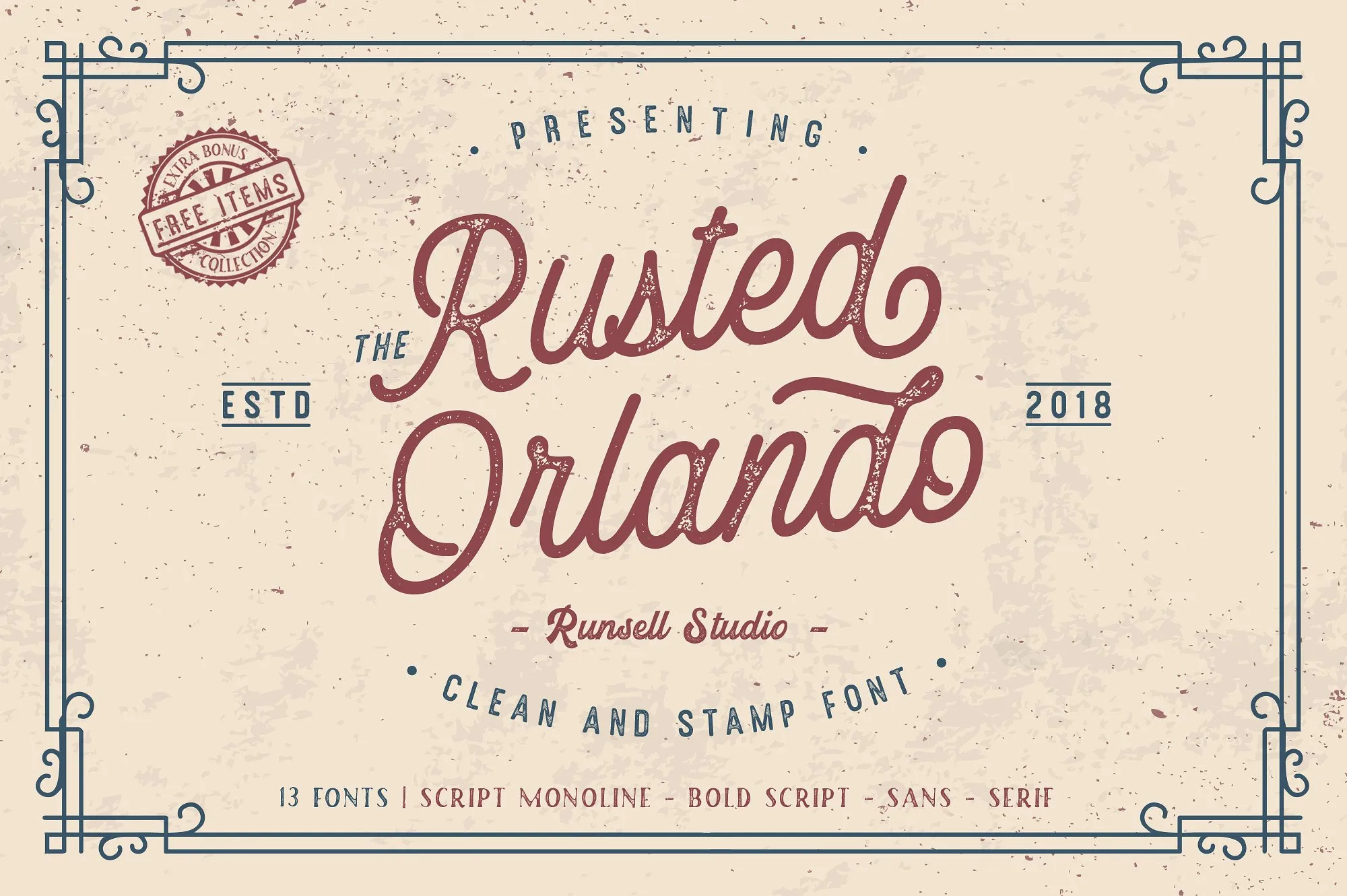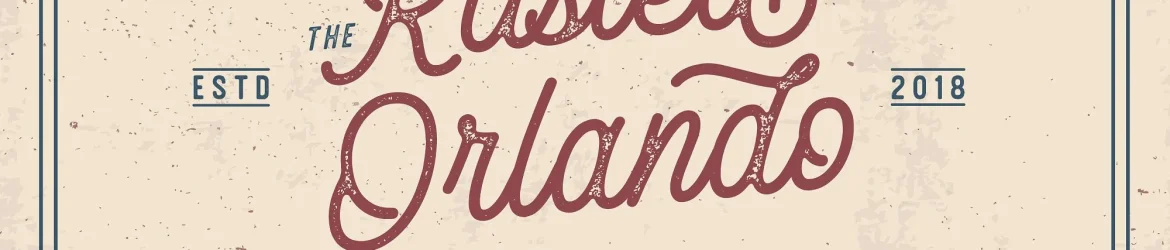
Rusted Orlando Font Family – Download Grátis
Introduzimos a família de fontes Rusted Orlando, que inclui uma ampla gama de opções: 13 fonts, incluindo um tipo script monoline, um tipo bold do script, e fontes sans-serif e serif. Esta família de fontes é perfeitamente adequada para várias aplicações, incluindo logotipos, marcação, embalagens, design de camisetas, além de muitas outras aplicações vintage. Esta opção vem com uma série de benefícios adicionais que auxiliam no desenvolvimento de projetos. Esses recursos abrangem desenhos (como um laboratório, um barbeiro, elementos da natureza, animais e veículos), ornamentos para molduras e emblemas bem como modelos templates de logotipos. É a escolha perfeita para designers que procuram algo vintage e único em suas criações.